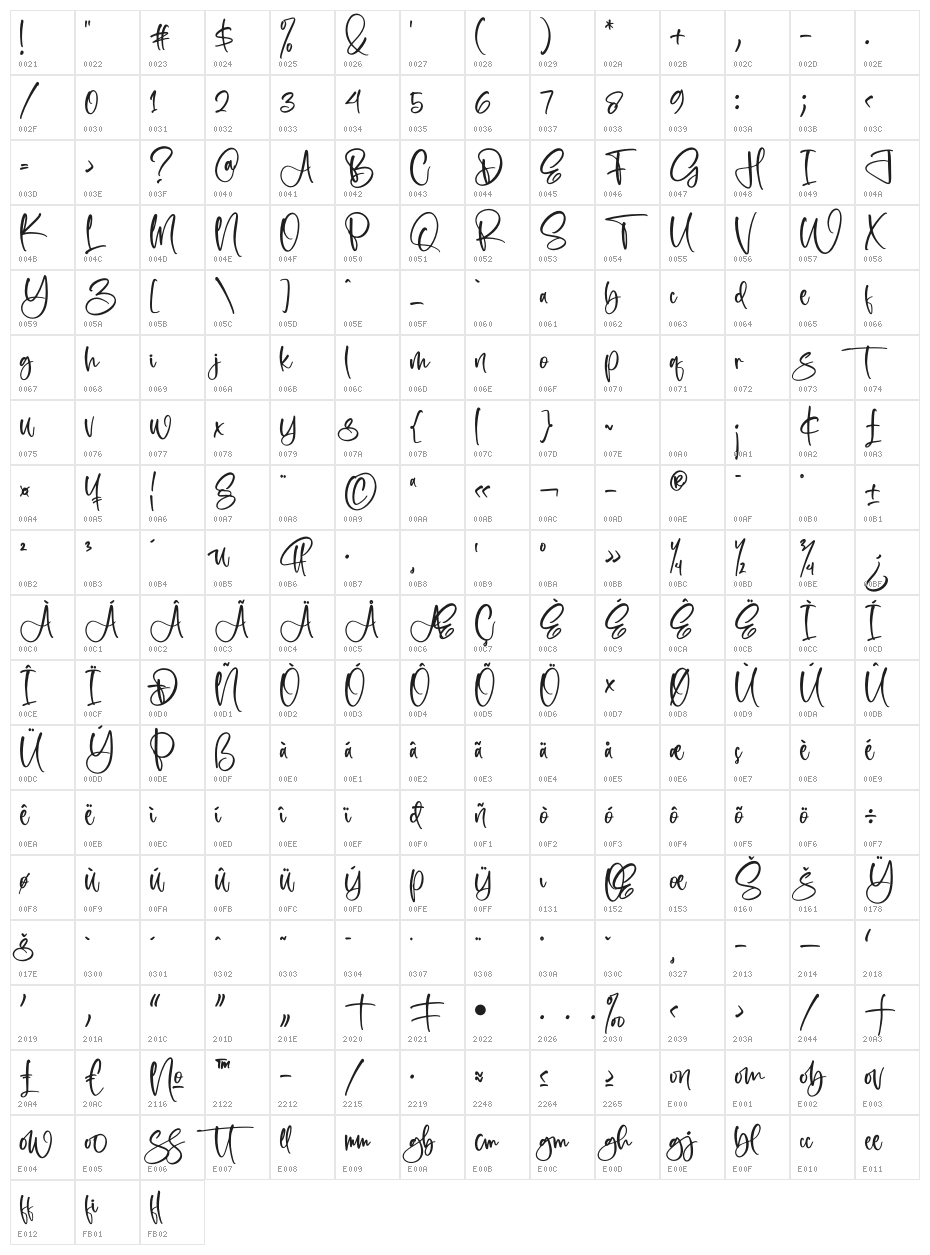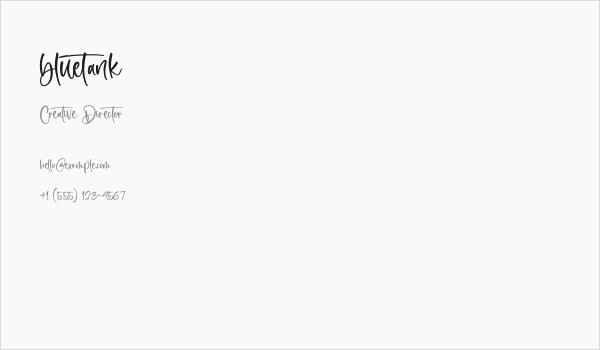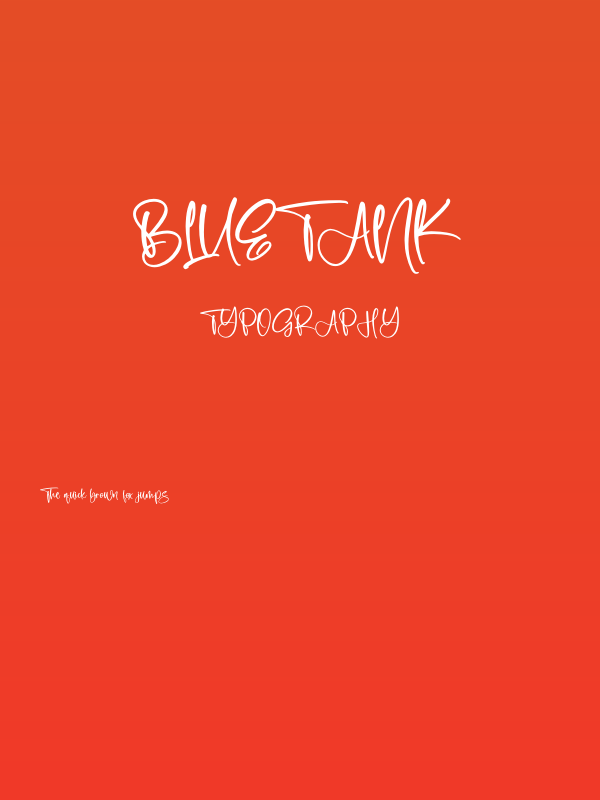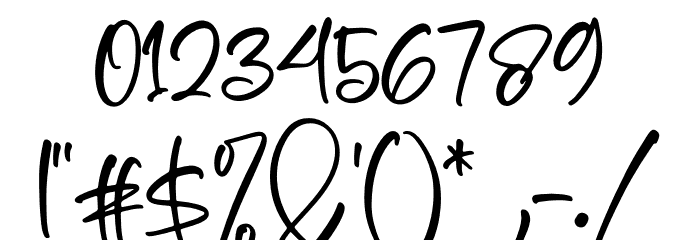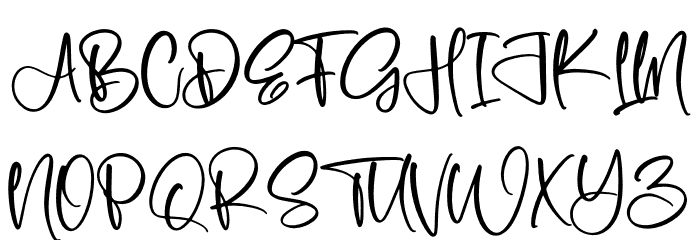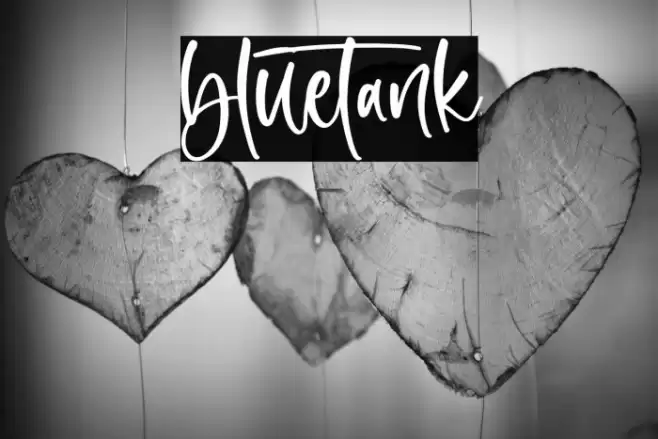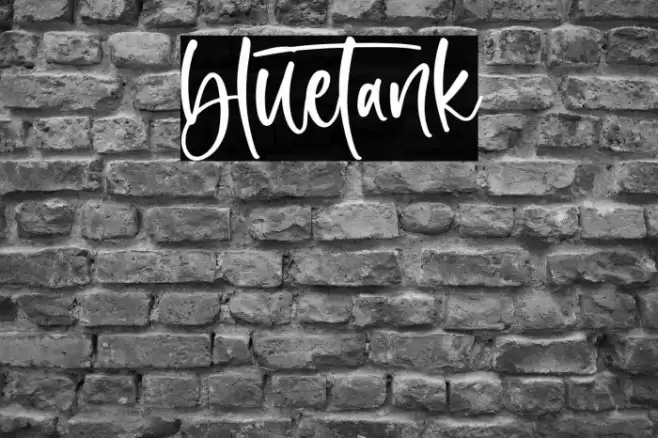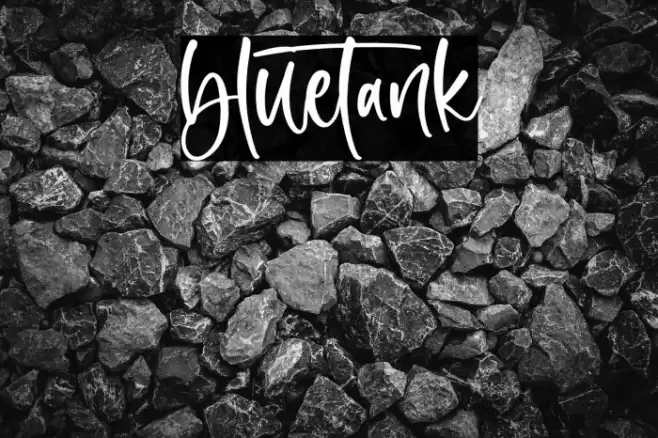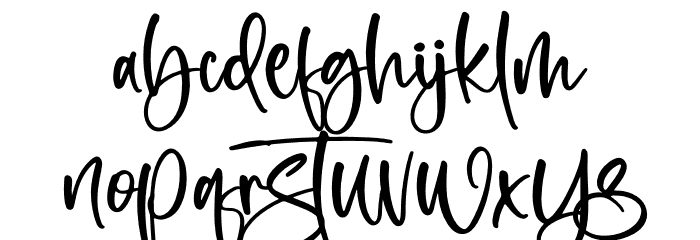
bluetank Font
| Anwendungsfall | Logos, Headlines, Creative projects |
| Vorgeschlagene Projekte | Ideal for greeting cards, invitations, personal branding, and creative social media graphics. |